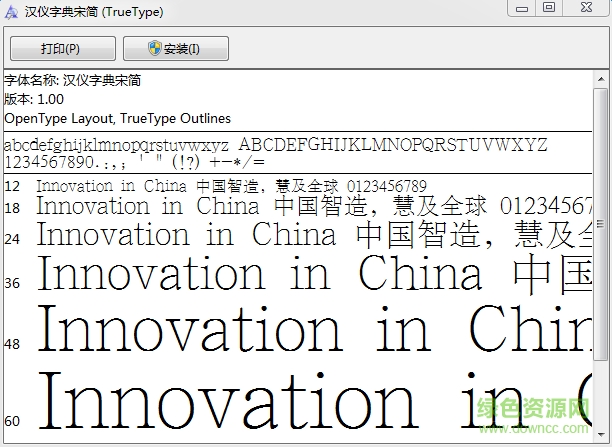
hya7gj字體也就是漢儀字典宋簡體字體,這款字體結(jié)構(gòu)簡潔大方,字形端正,能夠可以廣泛應用于廣告設計、宣傳海報,排版印刷等領域。需要的朋友歡迎來綠色資源網(wǎng)免費下載使用。
hya7gj字體是一款漢儀字體庫中的常用的字體,字型外觀整齊,功能性較強,整體效果非常出色,有喜歡的朋友就來綠色資源網(wǎng)下載使用吧!